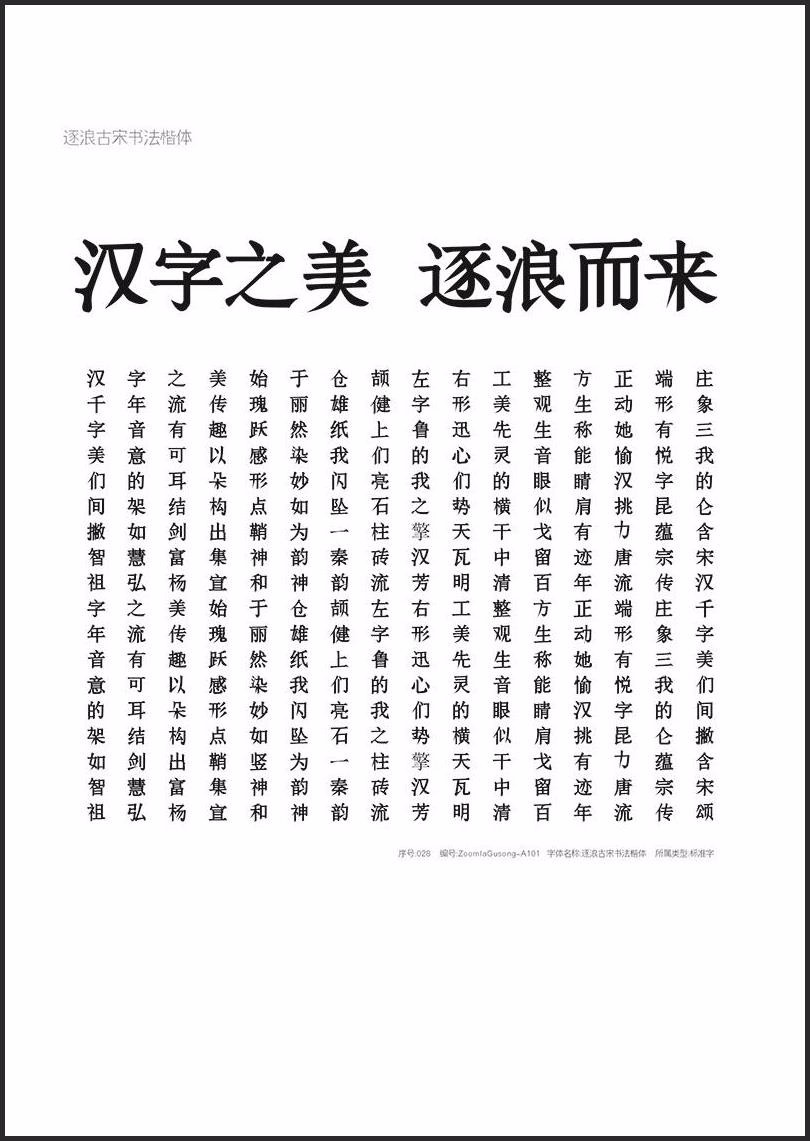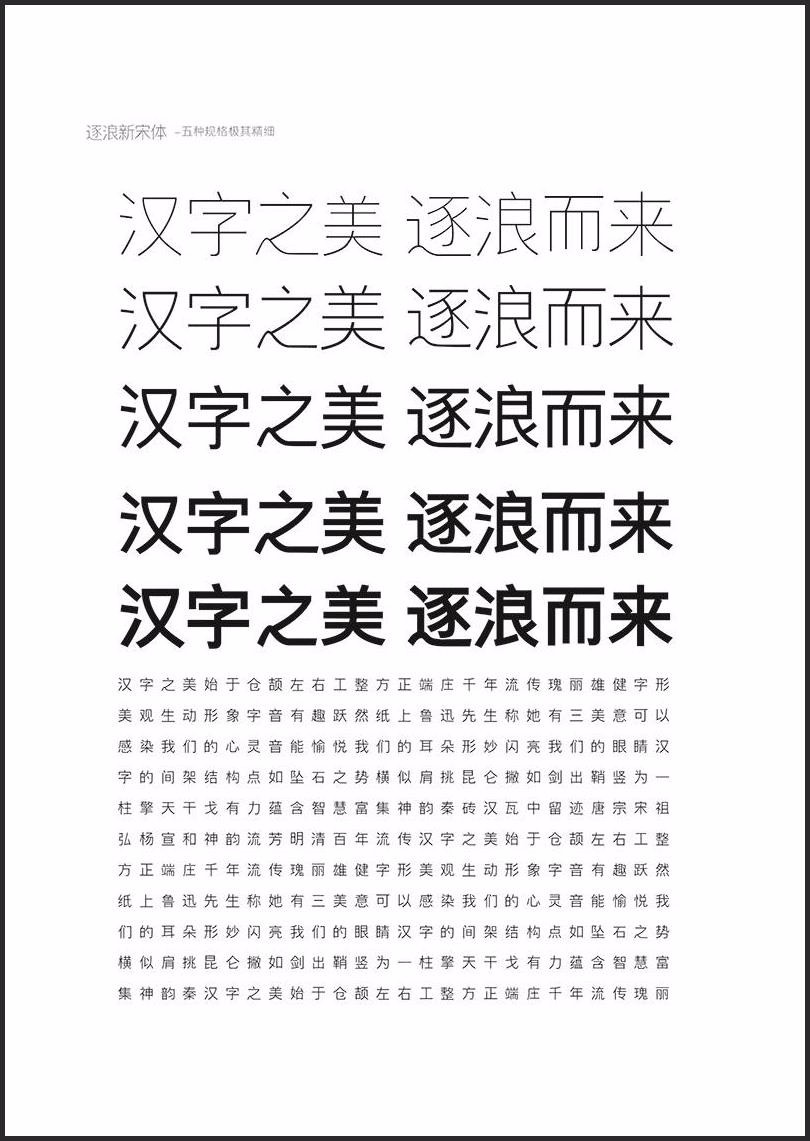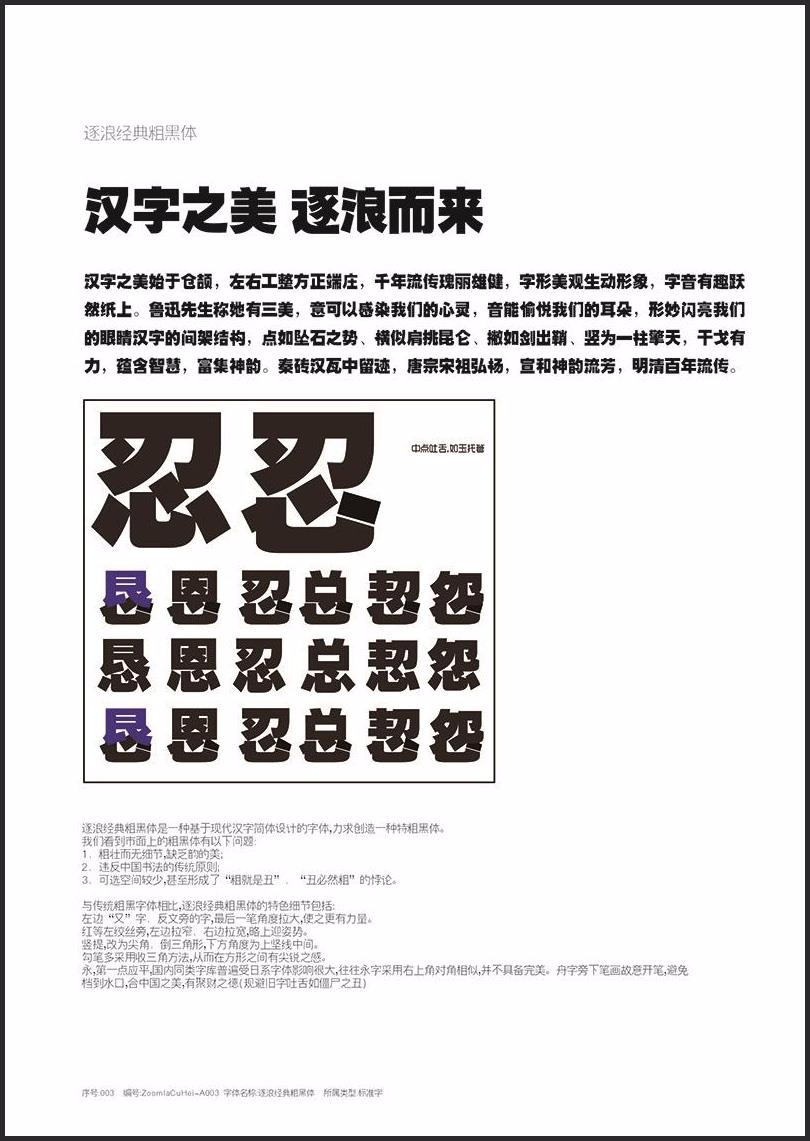
重磅:2018逐浪字库样本发布
逐浪字库是一家专门做字库研发、有自己独立的设计团队,有着自主的想法,不同的风格,在字体创作设计中有饱满的想法,给字体带来不一样的设计风格;在整个项目的设计中,我们力求于鲜活的人生体验相结合,从而在字形设计的过程中,变得非常有意思。
逐浪字库创办到现在已有12年以上的工作经验,弘扬华夏文明,专注中国字库研发-指的信赖的中文字库与书写研发团队。我们来自中国最大的内容管理系统与H5框架基础软件研发厂商-Zoomla!逐浪CMS团队,我们试图创造一个开放的、面向人人平等并传承汉字精华的字库体系。
逐浪字库正在一步步的成长,愿未来更美好!
逐浪花体:
本字体以纤瘦为线条为主,力求体现雅致效果。
每字均带花边,完美的曲线,使之表现能力趋强。
完全遵从汉字的设计理念,卓越表现。
逐浪投影透视黑体:
旷黑的世界,扭曲的光线,深遂的时空,独特的光线,构成本案设计理念。
独有的粗细对比,细处细如发丝、粗处黑暗压来,通过层叠的几何形状,构成本案字库设计理念,基于GB18030设计,为业界提供卓越的字库解决方案。
逐浪时尚钢笔体是一种基于现代汉字简体设计的字体,其原形是模仿传统硬笔(钢笔)写作效果,具有良好的应用场景和写作空间。
整个字体拥有以下特征:
全手写效果:整体上比市面上的字体更加纤细,以下为对比市面常用字体效果:
遵循汉字规范:严格按照汉字写作规范,而非为了创作而创作,并充份吸收了现代硬笔和政务文稿写填写的习惯,进行创作。
舒张大气:拥有时尚大气的体验,界面卓越。
整个定版字库共有8107个字符,未来还将不断扩充,从而构筑最优秀的硬笔写作字符体系。
整个创作过程,经历了前期策划è硬笔写作è电子扫描è矢量处理è入格优化è生成软件六个过程,历时三个多月,从而创造了一款较为优秀的硬笔行书体系。